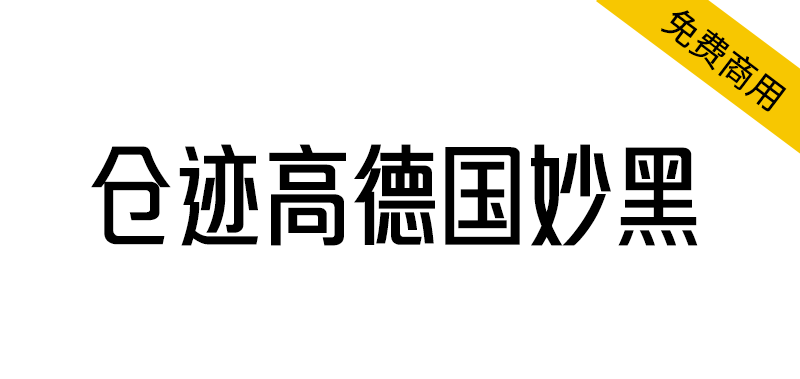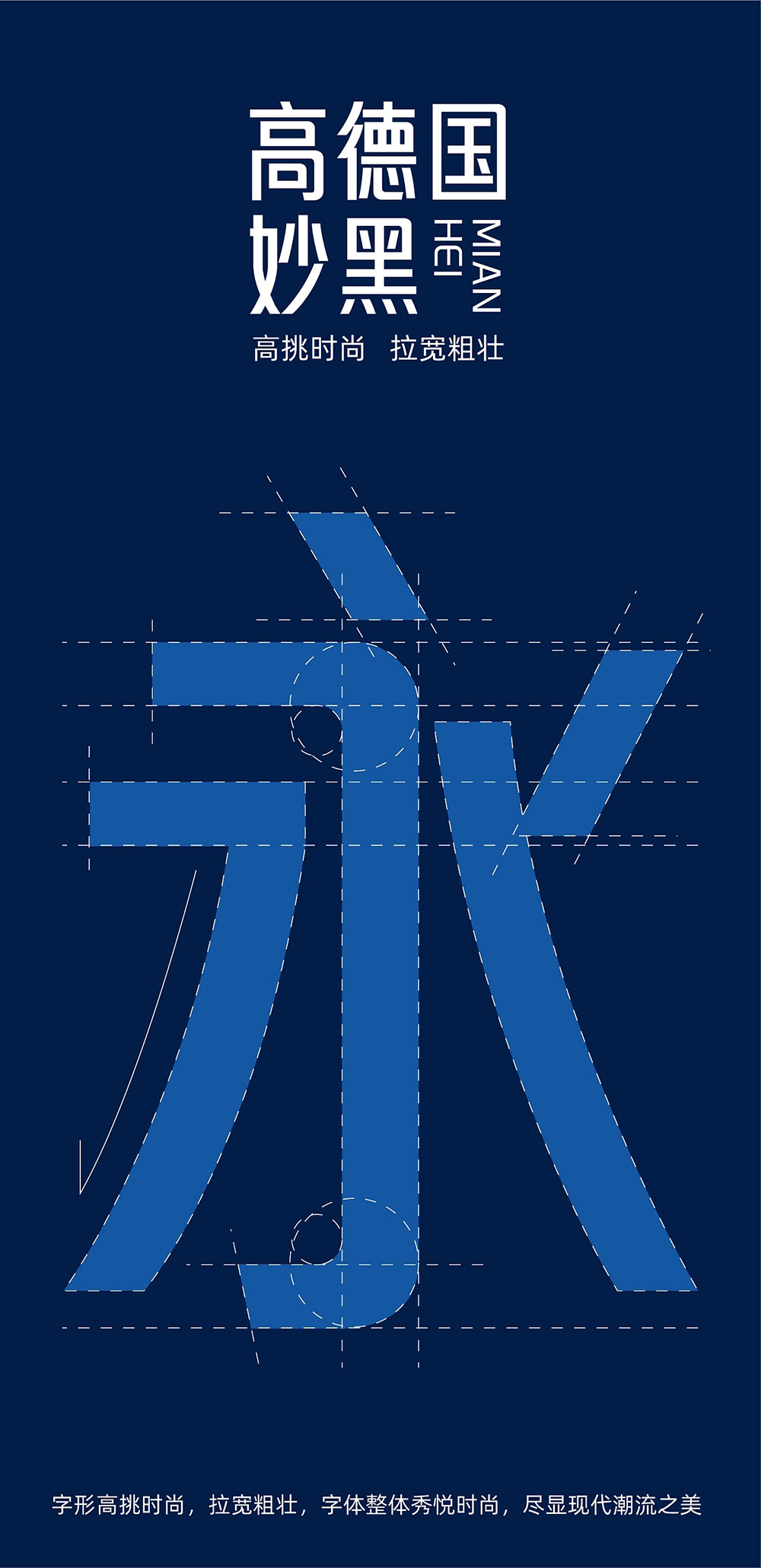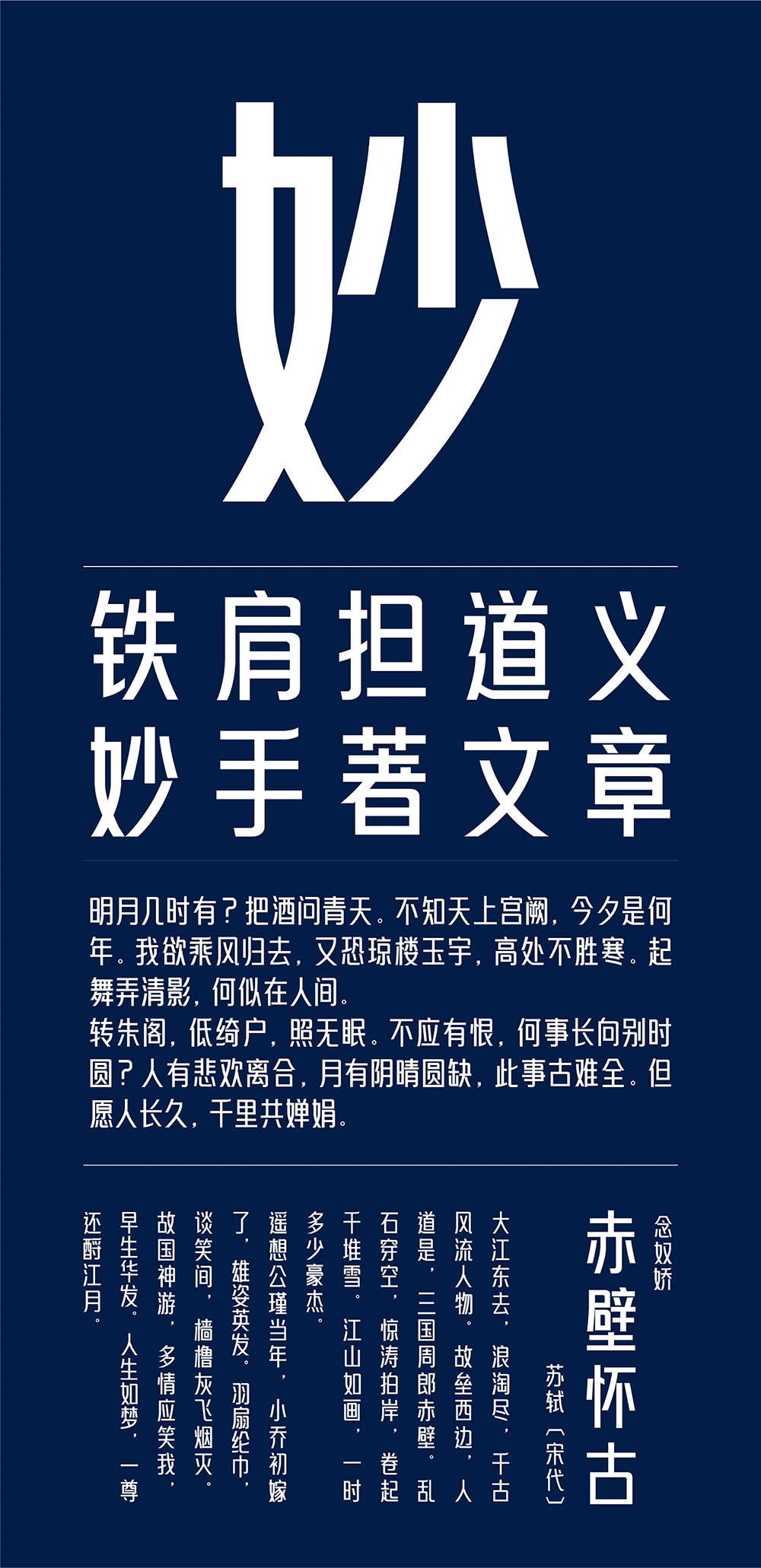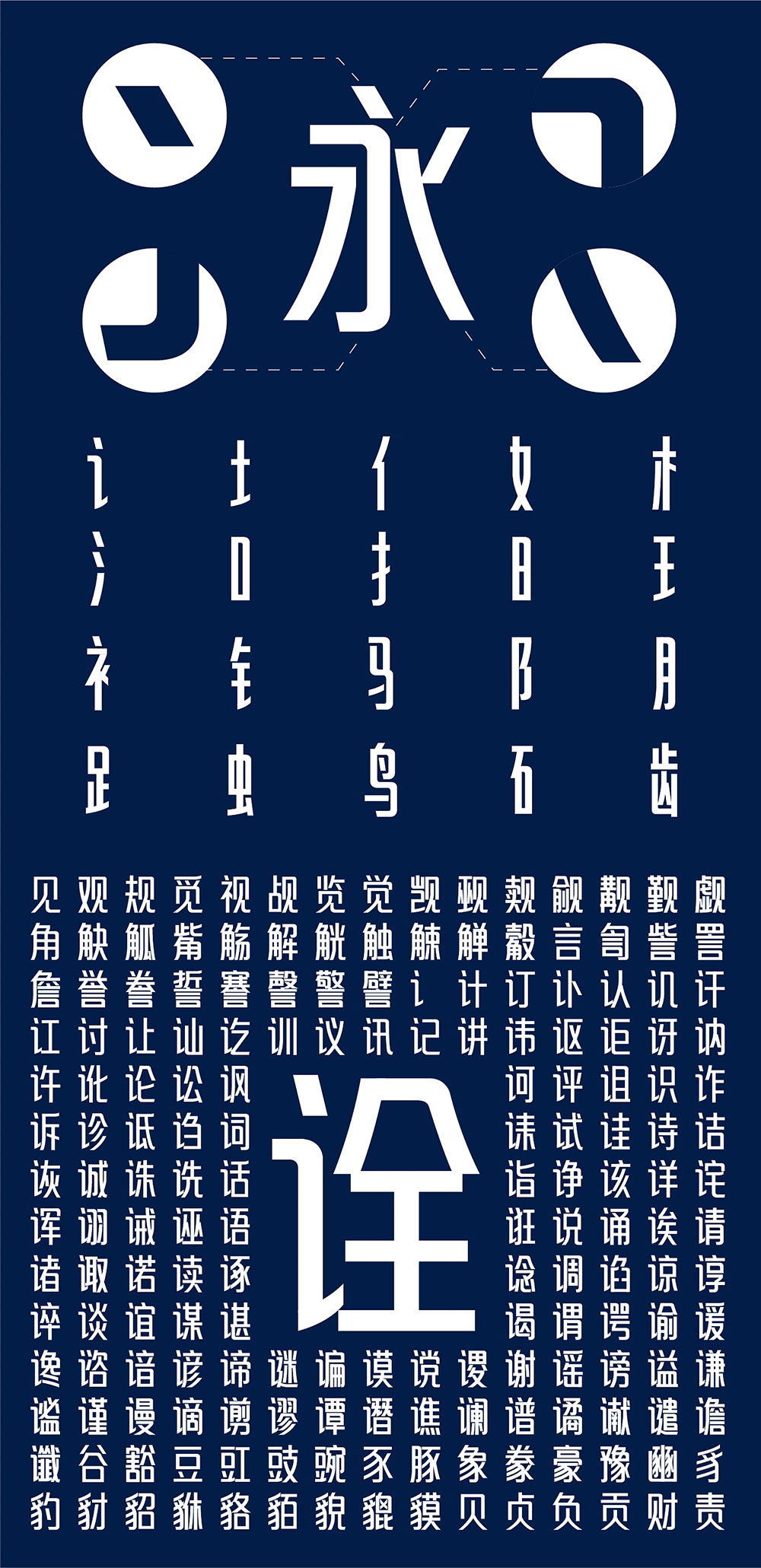
仓迹高德国妙黑体:这是一款收藏几年前的参赛样稿,从动笔到完工,陆续也有一年有余,总算能和大家见面了。当初这款字体有和字体厂商谈过,不过价格太低,我放弃合作,打算自己开发这款时尚感十足的字体,开发的时候其实几经修改,因为黑体款式比较多,稍微不注意就有撞车危险,感觉修改就是避坑,不管如何今天和大家见面了。
妙黑体高挑时尚,拉宽粗壮,做品牌设计必备,做广告标题良药,独特的高挑结构,使字体在商业创意设计中,可以更好的将字形与创意互相结合应用,能更好的为设计师服务,字体在各种行业众多场景都有出彩表现。
仓迹高德国妙黑,字库字数:7155字,字体风格:时尚、潮流型,适用范围:品牌标志、招牌、包装、海报、影视综艺、广告、游戏、漫画等。